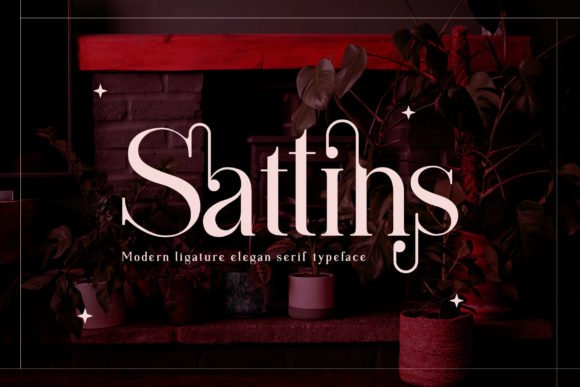
Название: Sattins Font (2021)
Sattins - это современный и выразительный шрифт с засечками.
Мастерски разработанный, чтобы стать настоящим фаворитом, этот шрифт способен поднять каждую из ваших творческих идей на самый высокий уровень!